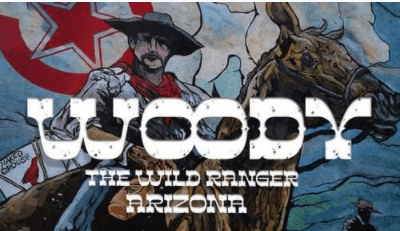
Retrocash Font
Эта пара была вдохновлена винтажным дизайном постера ковбойского фильма, который я видел в какой-то кофейне. Он был создан вручную специально, чтобы добавить естественного ощущения ручной работы в его фирменный стиль, чем я очищаю его с помощью Pentool.